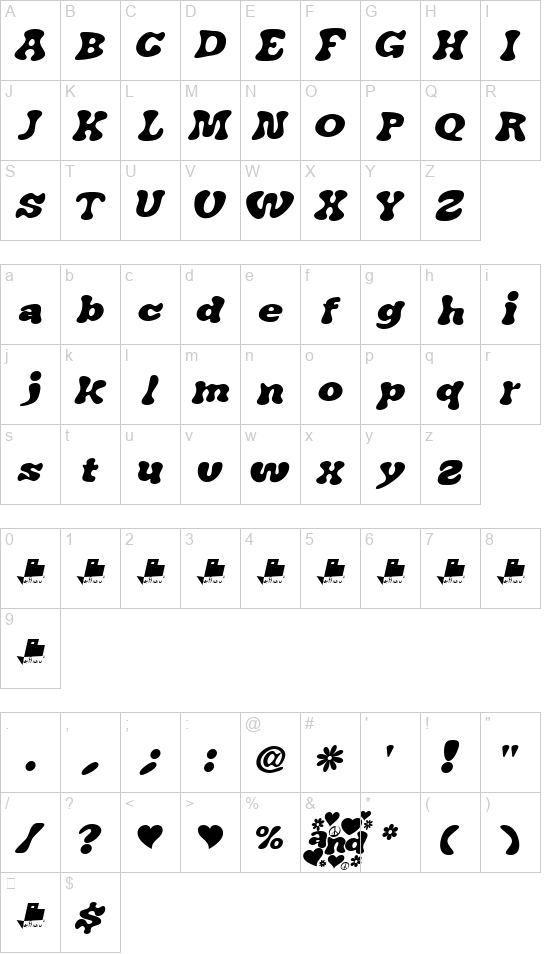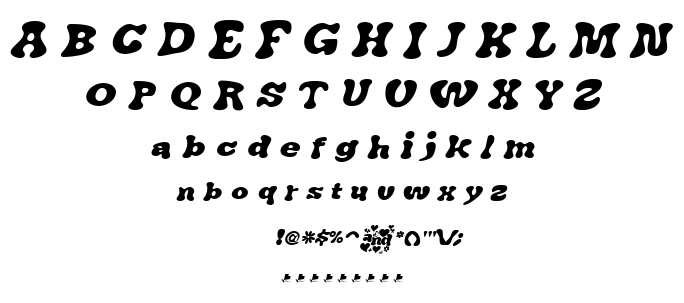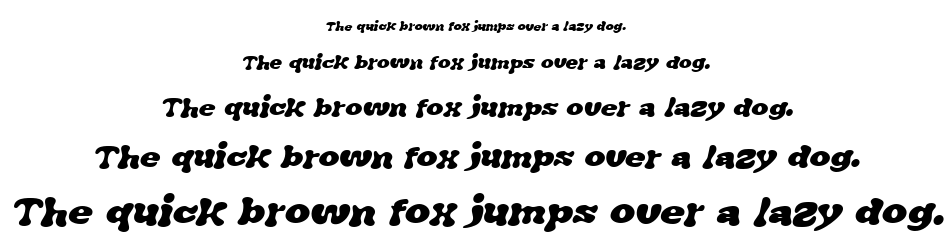
Tipografía de estilo psicodélico en homenaje a los años 60 y principalmente a los carteles tipográficos de conciertos de música pop de la época.
J. Airplane* es una fuente de estilo orgánico con Swashes.
Úsalos en combinación con las minúsculas: [] {} <> # * &
Ejem: J. A[irplane] Swash}